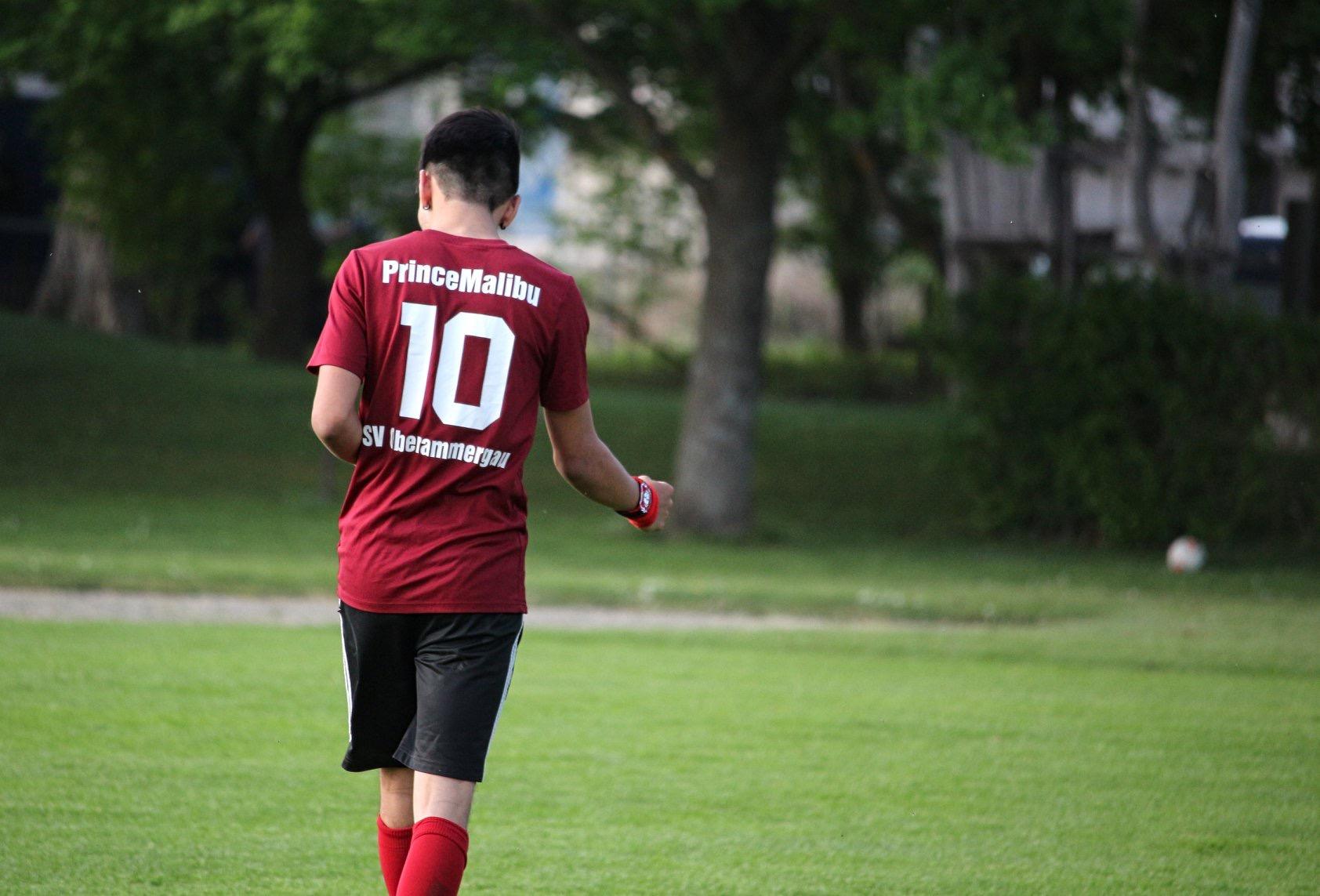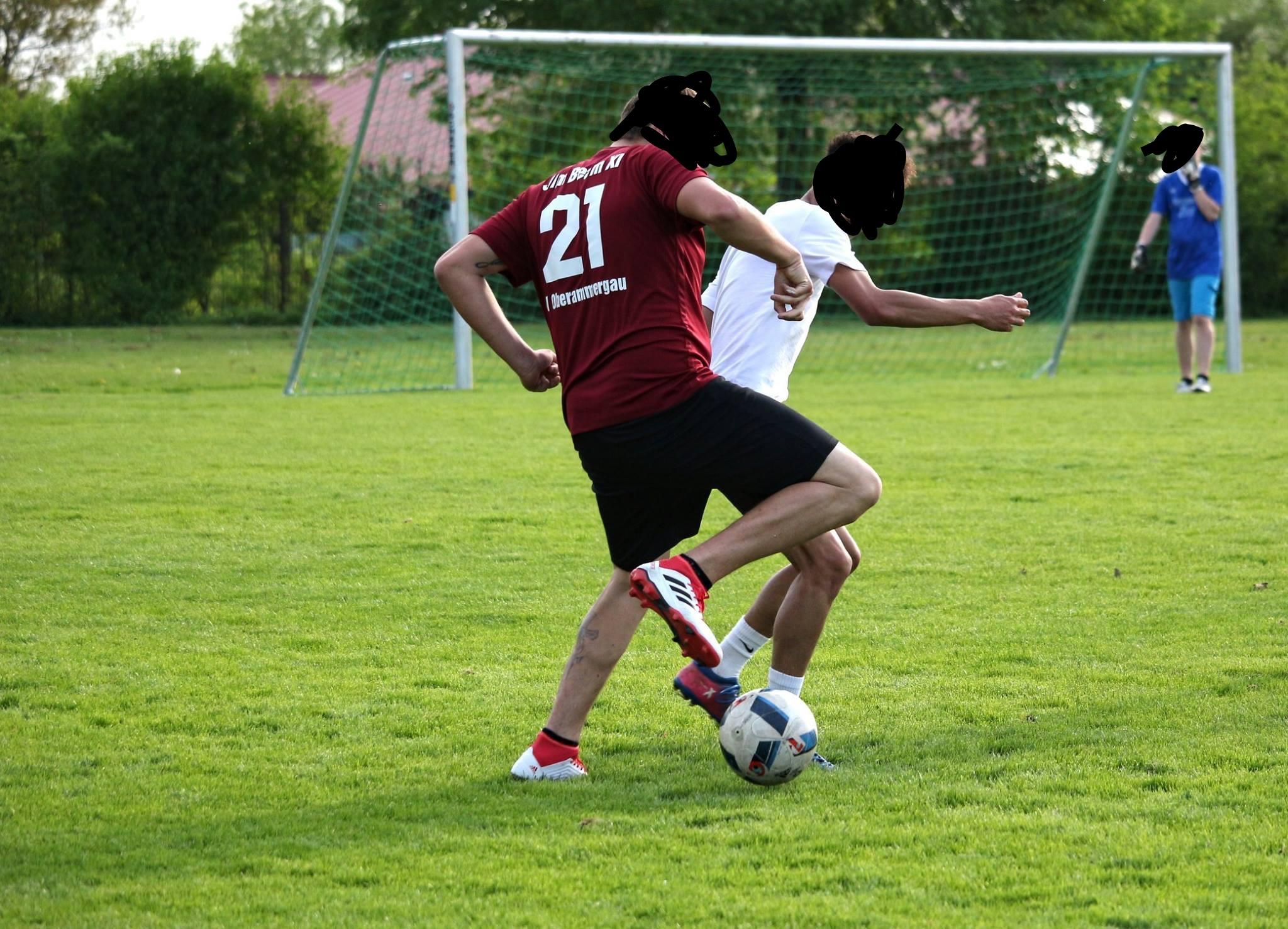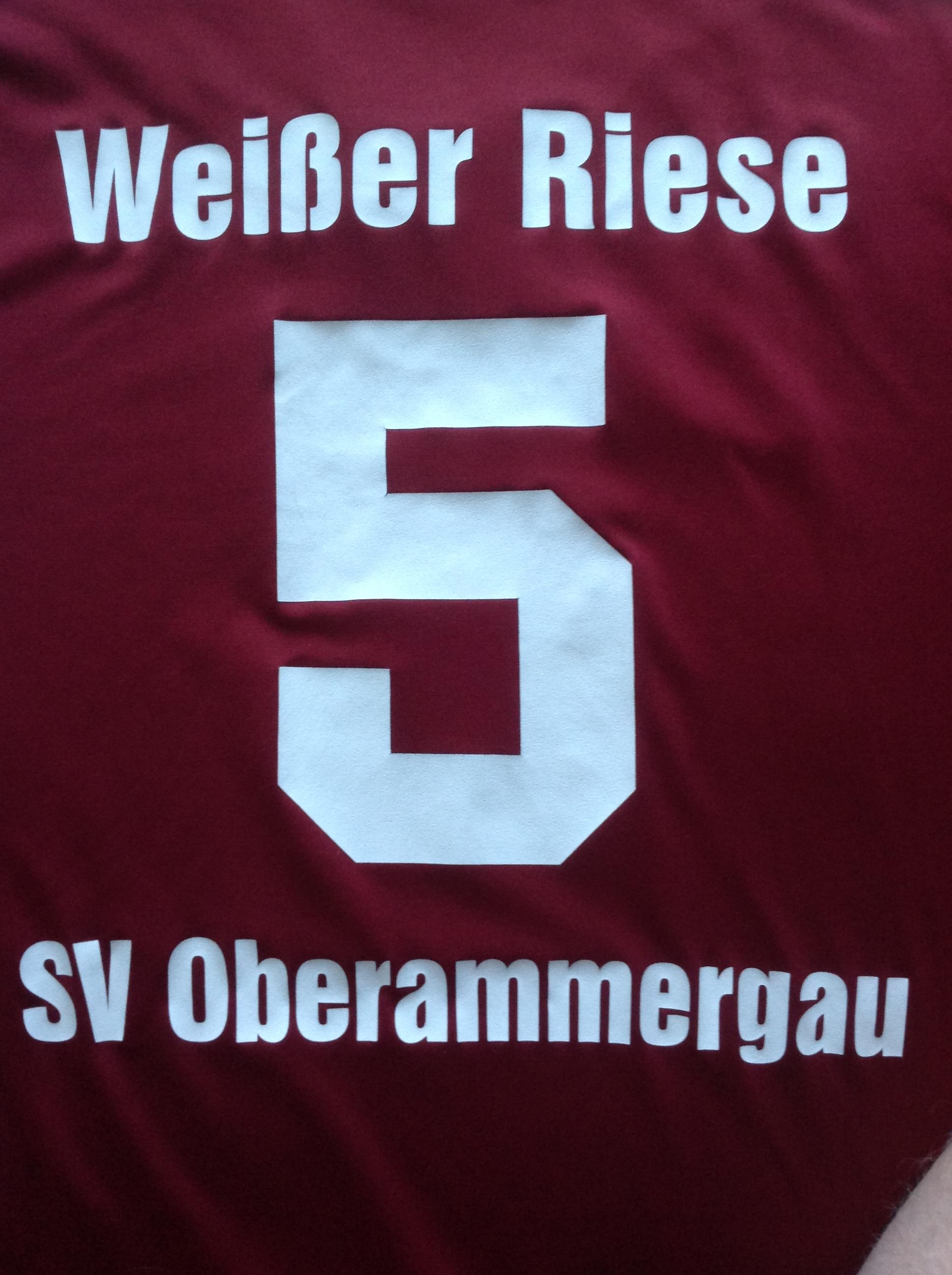
Suche Schriftart von bedrucktem Trikot
Wir haben vor 2 Jahren mit unserer Fußballmannschaft einen Satz Trikots bei einer Webseite bestellt und wollen nun einzelne Trikots davon ersetzen. Da man die Trikots dort nur als Satz bestellen kann, müssen wir die Trikots einzeln kaufen und selbst bedrucken lassen. Aus der möglichen Auswahl an Schriftarten bei der Bestellung kann ich leider nicht ausmachen welche Schrift damals verwendet wurde. Wäre super wenn mir jemand helfen könnte!
Ich suche:
Die verwendete (oder eine sehr ähnliche) Schriftart von dem Trikot auf dem Foto. Die Ziffer und der Schriftzug sind höchstwahrscheinlich verschiedene Schriftarten.
Informationen:
Die wählbaren Schriftarten auf der Seite sind:
Schriftart:
Swiss
DIN
Soho Med
Jersey
Barca
Ziffernart:
System
Block
Sport
Maino
Pisa
In deinem Fall wurde "Swiss" für den Text und "Block" für die Nummer gewählt.
Es scheint mir die "Swiss 921" zu entsprechen:
Hier sind noch einige Nummern, falls die 5 allein zu wenig ist.